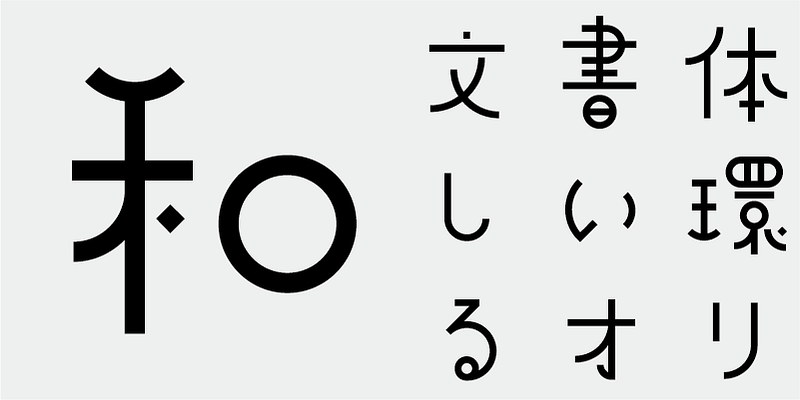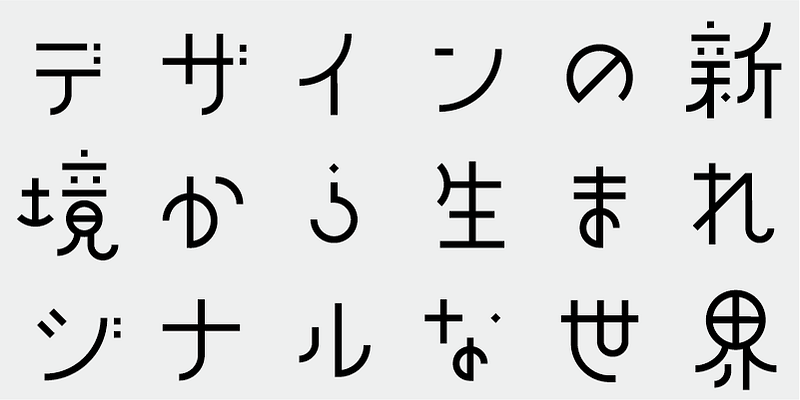
갓 쪼개진 대나무 향을 연상시키는 서체입니다. 서체 이름은 참새를 의미하며 대나무 숲에서 노는 참새 무리의 이미지에서 영감을 받았습니다.
영화나 TV의 타이틀, 타이틀 페이지, 패키지, 광고 캐치프레이즈 등에 유용한 디스플레이 서체입니다.
이 글꼴에는 신문사, 출판사, 언어 연구소가 만든 문자 빈도표에서 선정된 가장 많이 사용되는 일본어 한자 1,000개와 더불어 206개의 가나 문자와 구두점이 포함되어 있습니다.
오늘날 일본어 글꼴 제작에서는 JIS 표준의 7,000자가 필수로 간주됩니다. 그러나 모든 글꼴에 정말 7,000자가 필요할까요? 사진 식자 시대에는 훨씬 적은 수의 문자가 필요했습니다. 독립 서체 디자이너 그룹인 FONT1000은 그 간단한 질문으로 시작했습니다. 일본어 서체에 필요한 최소 1,000자의 한자(표의 문자)를 선택했고 이를 지원하는 서체와 글꼴을 적극적으로 만들었습니다. 이 1,000자의 한자 문자 세트는 신문사, 출판사, 언어 연구 기관 등에서 수집한 문자 빈도 데이터를 사용하여 선택되었으며 가나 음절 문자 및 구두점도 포함합니다. FONT1000은 2001년에 25명의 디자이너와 25개의 서체로 시작했습니다. 현재는 130개의 서체를 보유 중이고 거의 40명의 멤버를 포함하도록 성장했으며, 더 많은 문자가 있는 글꼴 작업이 가능하게 되었습니다.